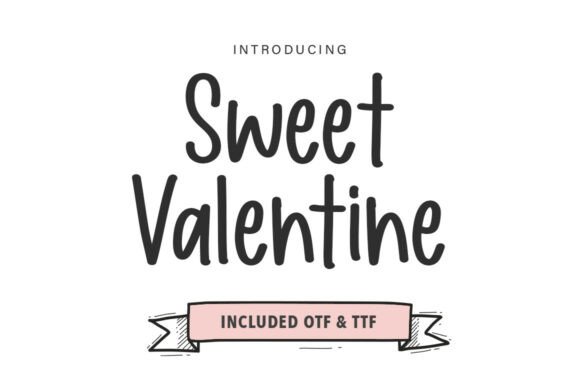
Sweet Valentine
Sweet Valentine์™€ ๊ฐ™์€ ๊ณ ํ’ˆ์งˆ ์ž์‚ฐ์„ ์ฐพ๊ณ  ์žˆ๋‹ค๋ฉด ์ด ํ”„๋ฆฌ๋ฏธ์—„ ํŒจํ‚ค์ง€๋Š” ์ฐฝ์˜์ ์ธ ํ”„๋กœ์ ํŠธ๋ฅผ ์œ„ํ•œ ํ™˜์ƒ์ ์ธ ์„ ํƒ์ž…๋‹ˆ๋‹ค.
POD(์ฃผ๋ฌธํ˜• ์ธ์‡„) ์ œํ’ˆ, ๊ฒฐํ˜ผ์‹ ์ดˆ๋Œ€์žฅ ๋˜๋Š” ์†Œ์…œ ๋ฏธ๋””์–ด ๊ทธ๋ž˜ํ”ฝ์„ ๋งŒ๋“ค ๋•Œ Sweet Valentine๋Š” ์ด์ƒ์ ์ธ ์„ ํƒ์ž…๋‹ˆ๋‹ค.